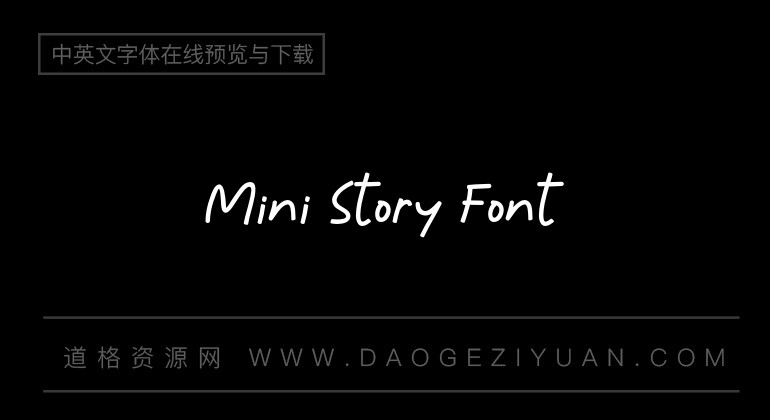
Mini Story Font
Mini Story Font 是一种由日本设计师 Kana Nakanishi 创作的手写风格字体。它的特点是线条清晰流畅,呈现出自然、轻盈、可爱的感觉。 这个字体的设计灵感来自于作者的日常生活和旅行经历,因此它的字形充满了温暖、自然的气息。Mini Story Font 的使用范围广泛,可以用于包装设计、海报、广告、文本排版等多种设计应用场景。
Mini Story Font是一款非常不错的手写艺术字体,具有很好的视觉感,适合于文化类的宣传设计、商业类品牌的广告和产品包装设计以及个性化文字排版等较多场景。